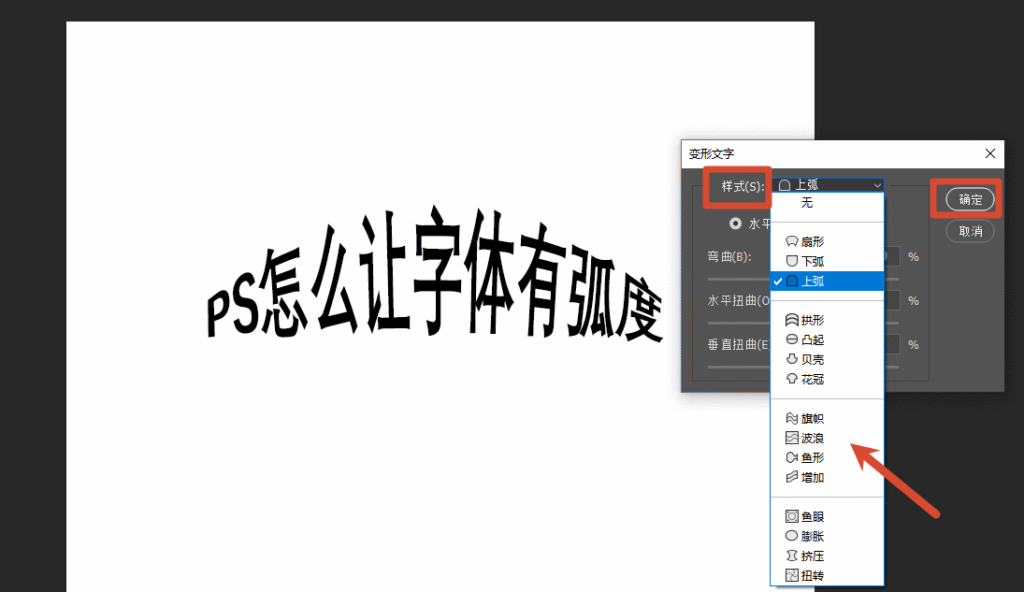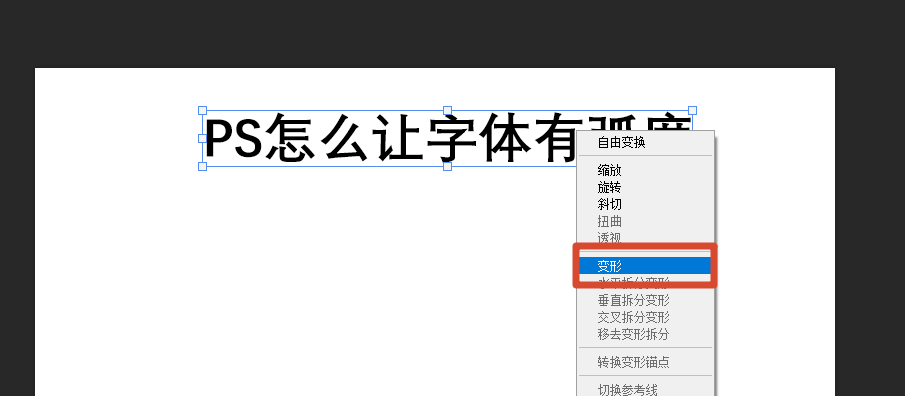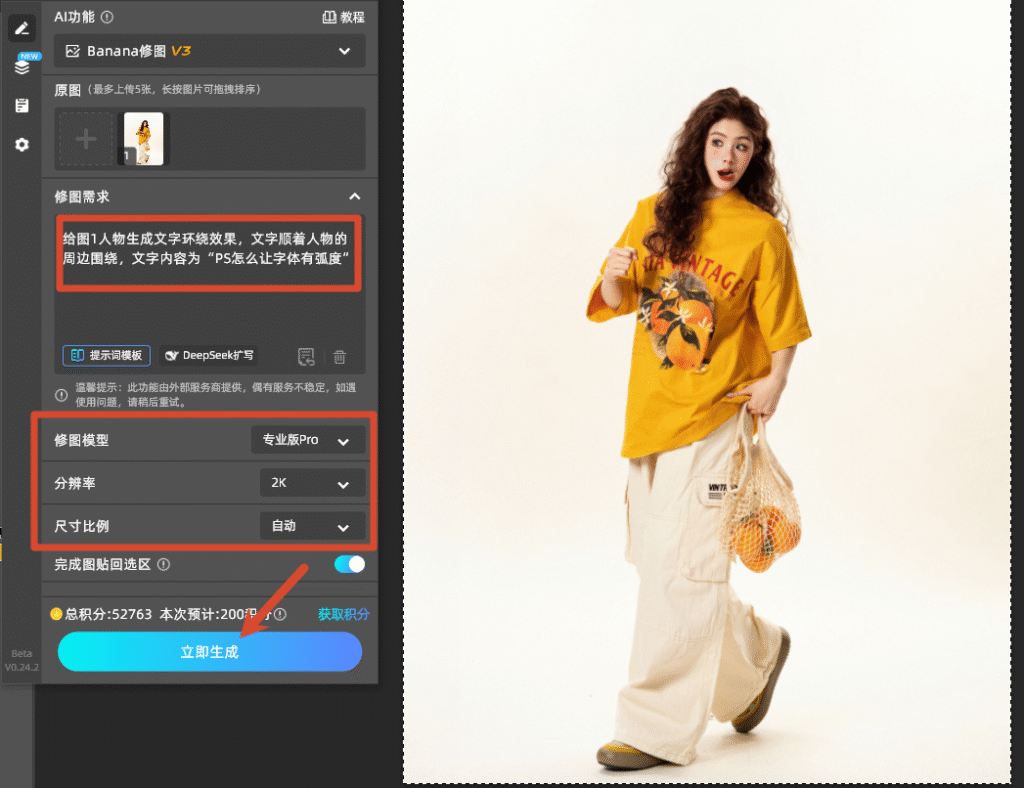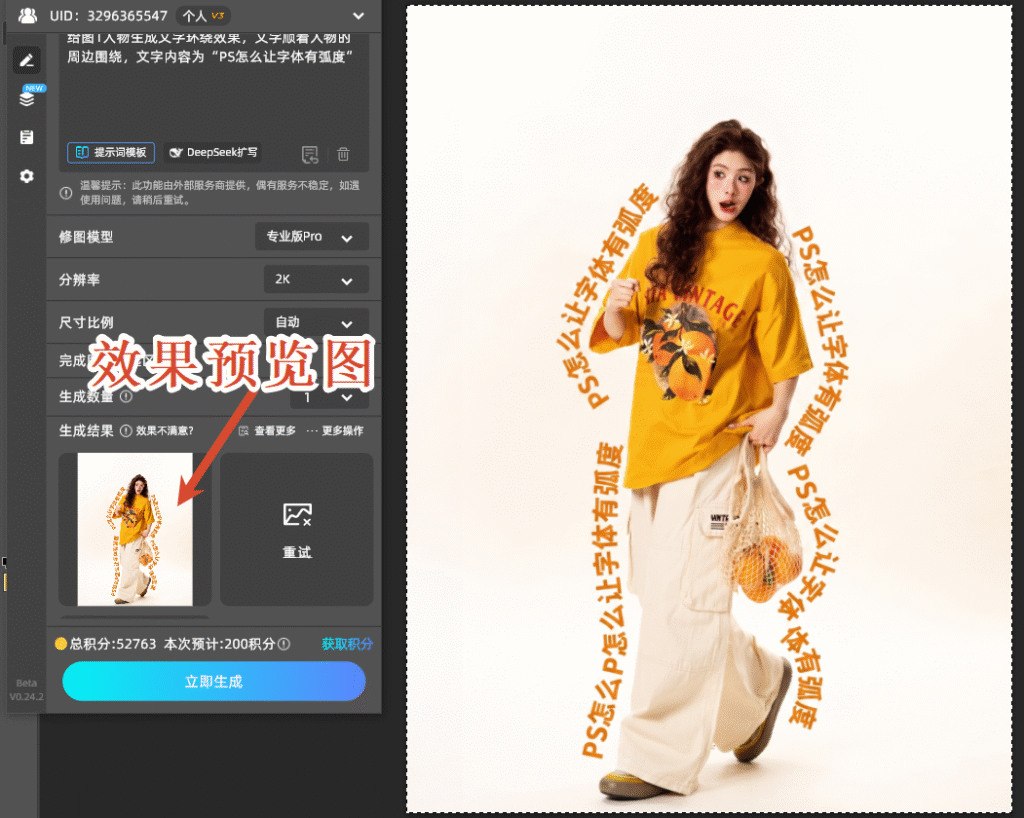
PS怎么让字体有弧度?3 种零基础实操方法
在海报设计、LOGO制作、电商主图、包装排版等设计场景中,弧形字体是高频常用的视觉排版方式,弯曲的文字能够贴合画面构图、提升设计层次感。很多设计新手常会疑惑:ps怎么让字体有弧度、PS如何把文字做成圆弧状、怎样制作环绕弧形文字。本文结合专业设计实操经验,分享3种零基础通用PS字体弧度制作方法,同时推荐新手友好的StartAI插件,解决PS字体弧度调整卡顿、变形生硬、操作复杂等痛点,轻松做出自然流畅的弧形文字。
一、3种原生PS方法,手动制作有弧度字体
针对不同弧形需求(简单单弧、环绕圆弧、自定义不规则弧度),整理三种官方原生操作方法,无需插件,纯手动调试,适合追求精准手动调整的用户。
方法一:文字变形工具(最简单,适合新手做规整弧度)
这是ps怎么让字体有弧度最简单的方法,无需绘制路径,一键套用弧形样式,适合海报标题、banner简约弧形文字,也是新手入门首选方式。
选中编辑好的文字图层,点击顶部属性栏中的【文字变形】图标(弯曲T型标识);
在弹出的设置窗口中,样式下拉列表选择拱形、下弧、上弧等弧形样式;
变形文字
拖动弯曲滑块调整弧度大小,常规设计建议数值控制在20%-50%,避免弧度过大导致文字变形失真;
微调水平扭曲、垂直扭曲参数,修正文字倾斜角度,预览无误后点击确定完成操作。
优缺点:操作耗时短、零门槛,但是弧度样式固定,仅支持规则弧形,无法制作个性化不规则弯曲文字。
方法二:自由变换变形(适合小众不规则弧度)
针对个性化异形弯曲字体,可使用自由变换功能,手动拖拽调整弧度形态,适合创意艺术字体设计。
选中文字图层,按下快捷键Ctrl+T开启自由变换模式;
右键点击画布,选择【变形】选项,调出网格调整框;
自由变换变形
手动拖拽网格锚点,按需拉扯出弧形、波浪形等自定义弧度;
调整完成后回车确认,微调文字边缘锯齿,优化视觉质感。
优缺点:创意性强,无固定弧度限制,但是手动把控难度高,容易出现字体拉伸模糊、比例失衡的情况。
二、StartAI插件一键制作弧度字体,新手零难度
1、StartAI插件操作步骤
选中需要制作的图层,无需栅格化、无需绘制路径;
选择Banana修图:填写修图需求“给图1人物生成文字环绕效果文字顺着人物的周边围绕,文字内容为‘PS怎么让字体有弧’”,选择修图模型、分辨率以及尺寸;
Banana修图
点击【立即生成】,1-3秒即可生成流畅弧形字体,自动优化字间距、倾斜度;
后期可二次微调光影、立体感,搭配投影、描边效果,提升字体高级感。
2、插件基础优势
• 极简操作:摒弃复杂锚点、路径调试,内置AI智能算法,一键生成自然弧度;
• 无损画质:区别于原生变形工具,AI智能保留字体像素质感,放大无模糊、无锯齿;
三、PS弧度字体制作注意事项
1. 日常简约排版优先使用文字变形工具,圆形LOGO优先搭配StartAI环绕弧度模板,减少手动锚点调试;
2. 字体弧度数值不宜过大,常规排版弯曲度控制在15%-40%,避免文字扭曲变形、可读性下降;
3. 低配置电脑尽量使用StartAI插件,原生路径工具容易出现卡顿、闪退问题;
4. 弧形字体导出保存时,优先选择PNG透明格式,保留边缘质感,避免压缩模糊。
四、总结
以上就是ps怎么让字体有弧度的全套实操教程,三种原生方法适配不同设计场景:新手快速排版用文字变形、专业LOGO用路径工具、创意设计用自由变换。如果想要降低操作门槛、提升出图效率,StartAI插件是最优选择,依托AI智能算法优化字体弧度,兼顾画质、速度与美观度,无需专业设计基础,人人都能做出高级流畅的弧形文字。
无论是电商美工、自媒体创作者,还是设计新手,都可以搭配原生工具+StartAI插件组合使用,高效解决PS字体弯曲、排版美化难题,轻松提升设计作品质感。